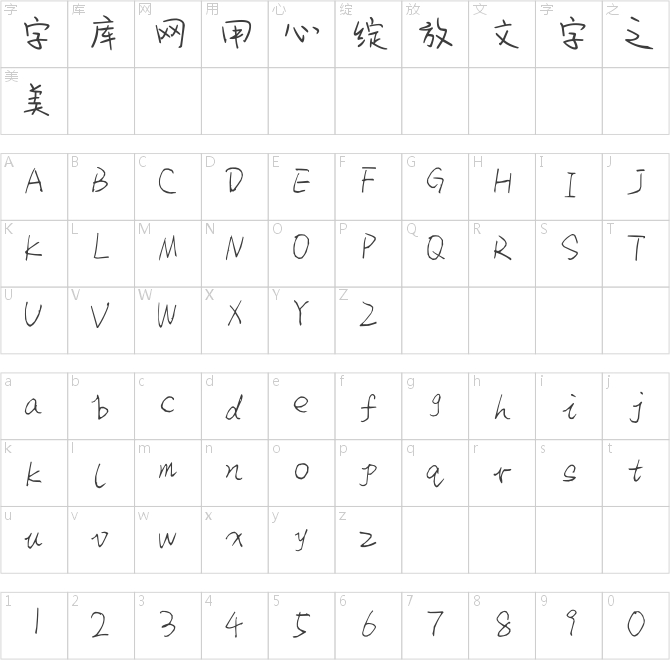
字體名稱: SNH48黃婷
SNH48黃婷婷
SNH48黃婷婷字體方正手跡-SNH48黃婷婷字庫(kù)是一款讓人賞心悅目、百看不厭的中文字體,適合各類廣告和產(chǎn)品包裝設(shè)計(jì)應(yīng)用,字體大小2.31MB,格式為ttf字體,上傳用戶是Honor,作者/版權(quán)方為方正